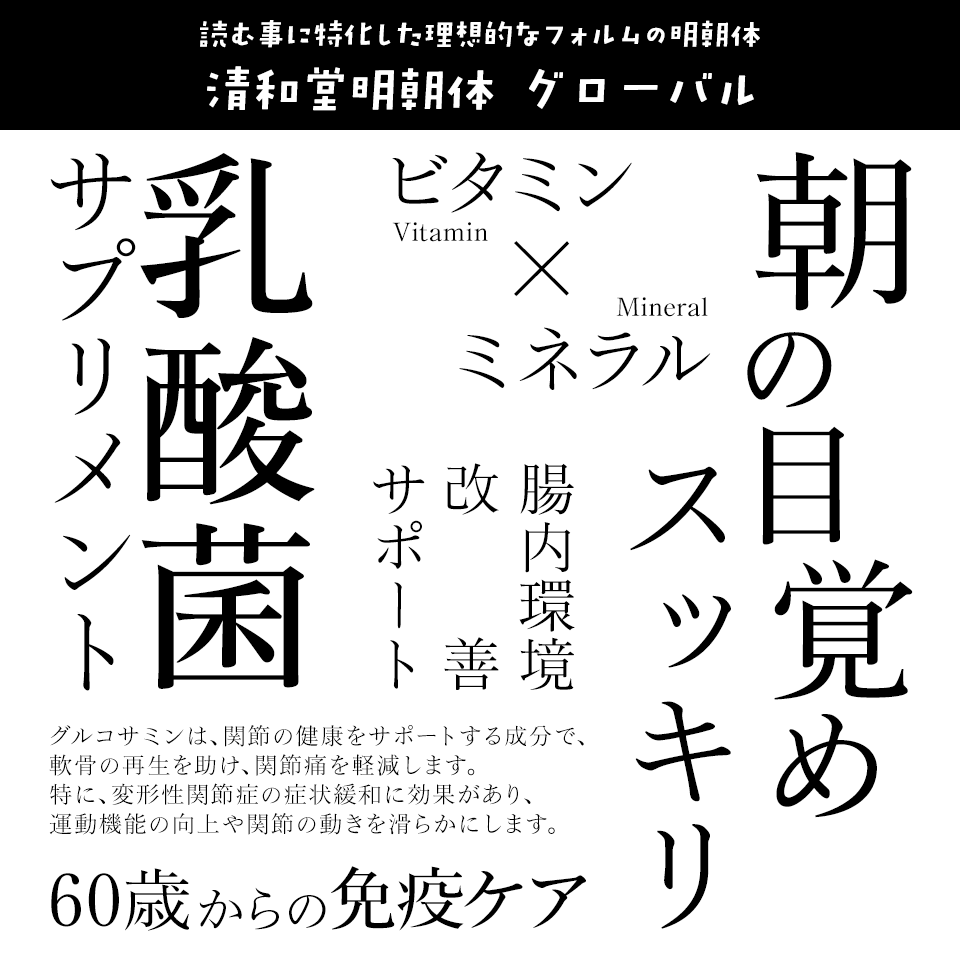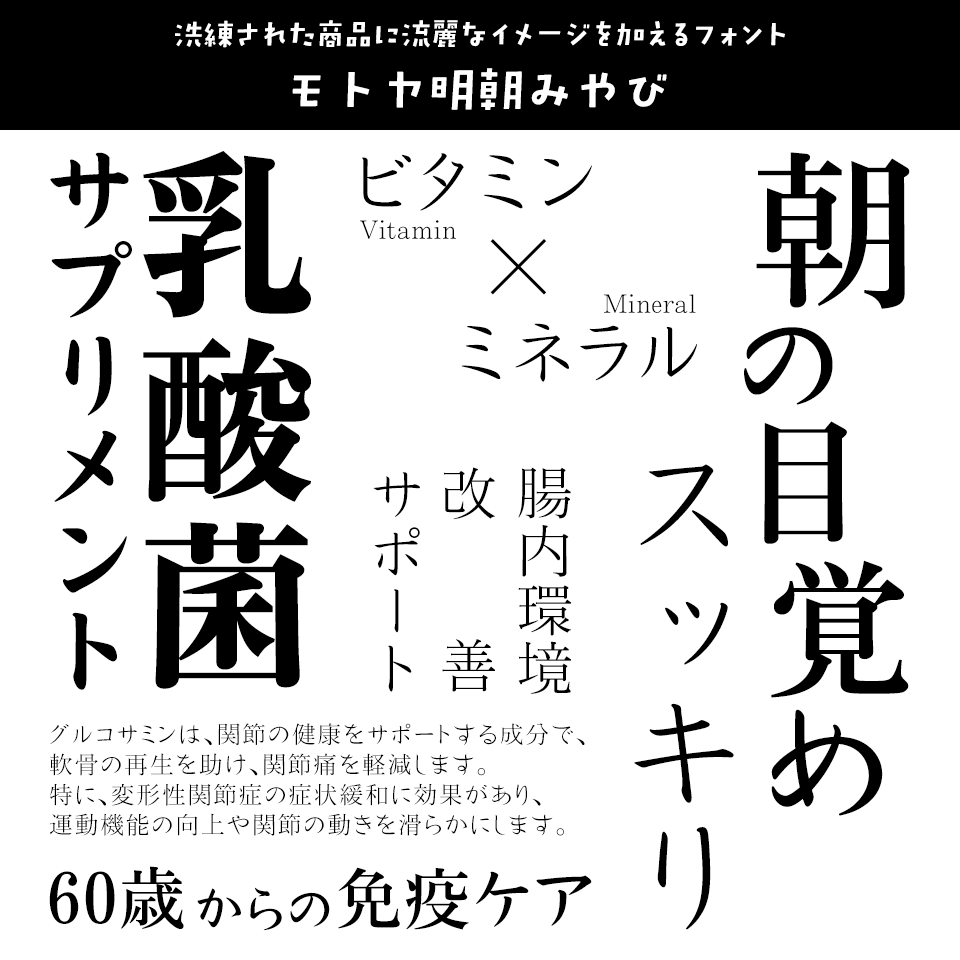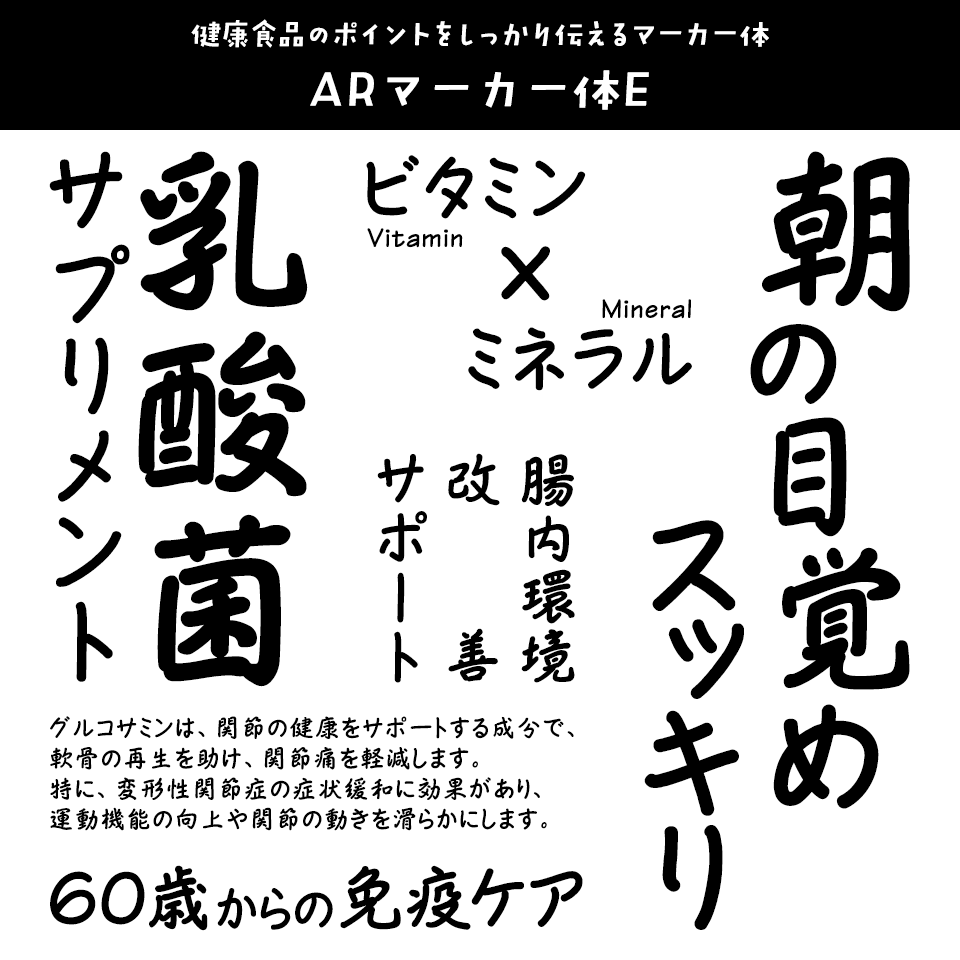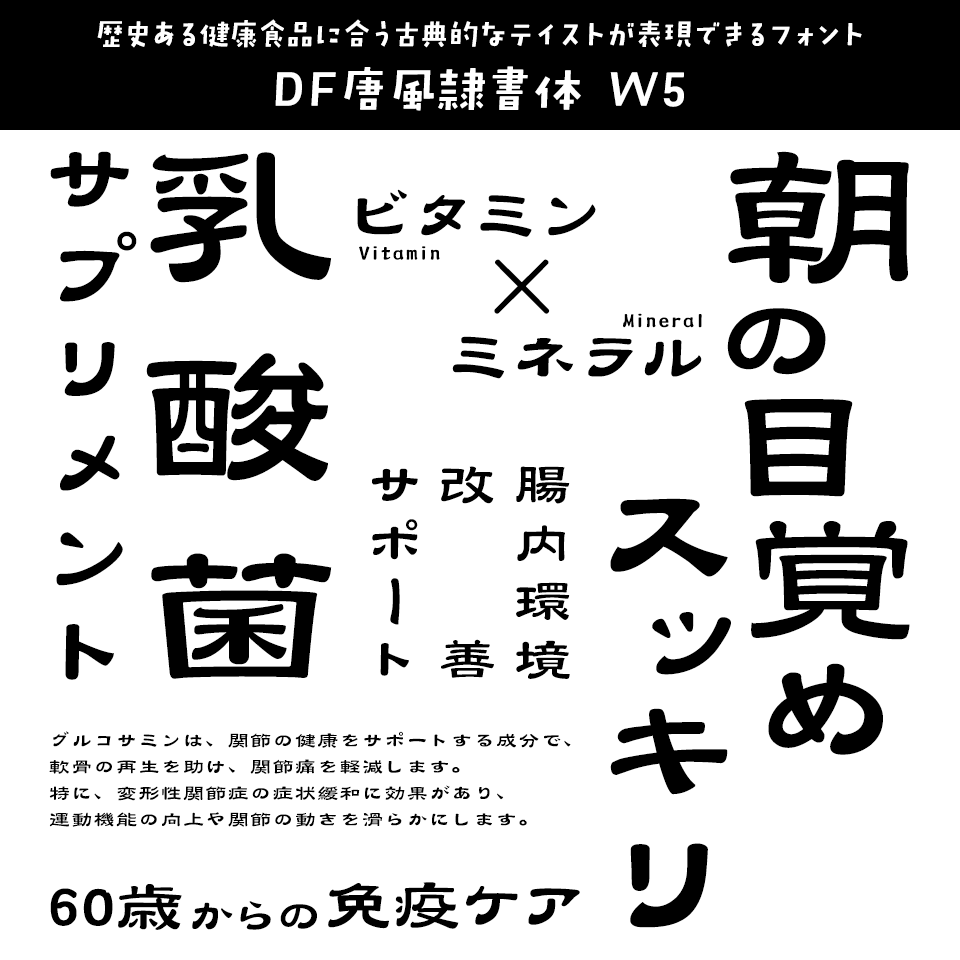
「健康食品」に合うフォント:特化型 目的別フォントガイド #143
今回は「健康食品」に合うフォント。日々フォントのことばかり考えている当店スタッフが直感的に選んだフォントをご紹介します。
「健康食品」に合うフォントをスタッフが選びました
「健康食品」に合うフォント DFひびゴシック
お悩みの訴求に使えるひびの入ったフォント
DFひびゴシック【ダイナフォント】
「健康食品」に合うフォント DFひびゴシック
健康食品の説明に不可欠なビフォーアフター。ビフォーの表現に使える不穏なひびの入ったデザインフォントです。
「健康食品」に合うフォント 清和堂明朝体 グローバル
読む事に特化した理想的なフォルムの明朝体
清和堂明朝体 グローバル【清和堂】
「健康食品」に合うフォント 清和堂明朝体 グローバル
清和堂明朝体フラッグシップ書体として、それぞれの文字固有の形を大事にしながら、標準性・汎用性、無駄がない鍛えあげたボディ、Bauhausによる「形体は機能に従う」という基本思想を追いかけ続け、読む事に特化した理想的なフォルムを追求しました。
「健康食品」に合うフォント DF娥眉明朝体
清潔感や高級感ある商品の演出におすすめ
DF娥眉明朝体【ダイナフォント】
「健康食品」に合うフォント DF娥眉明朝体
細長く弧を描いた眉の形をイメージしたストロークから洗練された女性の柔らかさや優しさを表現した明朝体の書体。清潔感や高級感ある商品の演出などに優れています。
「健康食品」に合うフォント KOはなぶさ蛍雪M
高級感のある健康食品に合う伝統に基づいたフォント
KOはなぶさ蛍雪M【欣喜堂】
「健康食品」に合うフォント KOはなぶさ蛍雪M
蛍雪『欽定全唐文』(董詰編、1814年、揚州詩局)より再生した清朝官刻体「蛍雪」、K.E.Taurus『ミラノ君主ヴィスコンティ家列伝』(1549年)より再生したオールド・ローマン体に、『少年工芸文庫第八編』(石井研堂著、1902年、博文館)より再生した和字書体「はなぶさ」を組み合わせた伝統に基づいた新たな活字書体です。
「健康食品」に合うフォント ヒラギノ明朝
チラシやLPのタイトルから本文までこなす定番の明朝体
ヒラギノ明朝【ヒラギノフォント】
「健康食品」に合うフォント ヒラギノ明朝
時代に左右されない普遍的な美しさを持ち、1993年の発売以来様々なシーンで使われ続けているスタンダードな明朝体です。 なめらかで切れ味のあるフォルムと、画線同士の空間が一定になるような細かな調整により、広告、ポスター、パンフレット、雑誌など、現代のあらゆるグラフィックデザインに調和します。
「健康食品」に合うフォント モトヤ明朝みやび
洗練された商品に流麗なイメージを加えるフォント
モトヤ明朝みやび【モトヤ】
「健康食品」に合うフォント モトヤ明朝みやび
みやびシリーズは流麗な仮名デザインで、文章に柔らかい表情を加えることができます。健康食品のパッケージや紹介文に使用すると、印象が向上すると思います!
「健康食品」に合うフォント 東亜重工 GRUNGE
グランジ加工で悩む心境を表現
東亜重工 GRUNGE【イワタ書体ライブラリー】
「健康食品」に合うフォント 東亜重工 GRUNGE
「東亜重工GRUNGE」は、東亜重工製フォント『東亜重工』にグランジ(汚れ)加工を施したフォントです。デザインソフトなしでもステッカーなどの印刷物や画像にアクセントをつけることが可能です。
「健康食品」に合うフォント イワタミンゴ
スッキリと読みやすい洗練されたモダンな書体
イワタミンゴ【イワタ書体ライブラリー】
「健康食品」に合うフォント イワタミンゴ
明朝体のシャープさ・可読性の良さと、ゴシック体の強さ・整斉さを兼ね備えた、スッキリと読みやすいデザインの格調ある書体です。
「健康食品」に合うフォント DSサラ
健康食品にぴったりのナチュラルな書体
DSサラ【七種泰史/デザインシグナル】
「健康食品」に合うフォント DSサラ
さらりサラサラ。すっきり、あっさり味の書体。健康食品のイメージに合う細めでナチュラルな印象のデザインが特徴です。
「健康食品」に合うフォント DF平成ゴシック体R W7
説得力なら太めのゴシック体
DF平成ゴシック体R W7【ダイナフォント】
「健康食品」に合うフォント DF平成ゴシック体R W7
健康食品の効能に説得力を持たせるのにぴったりな太めのゴシック体です。
「健康食品」に合うフォント ARマーカー体E
健康食品のポイントをしっかり伝えるマーカー体
ARマーカー体E【アーフィック】
「健康食品」に合うフォント ARマーカー体E
見出しやタイトル、吹き出しのコメントなど、健康食品のチラシやLPの様々な場所で使いやすいフェルトペンで書いたタッチの手書き風書体です。
「健康食品」に合うフォント TA 石ちゃん
ガラガラと崩れる健康状態に
TA 石ちゃん【FONT1000】
「健康食品」に合うフォント TA 石ちゃん
大きな石を削って文字を作ったイメージです。荒々しいフォルムですので、フォント名は逆に馴染み易くしました。崩れる生活習慣のに、粗削りな輪郭のフォントを。
「健康食品」に合うフォント DF唐風隷書体 W5
歴史ある健康食品に合う古典的なテイストが表現できるフォント
DF唐風隷書体 W5【ダイナフォント】
「健康食品」に合うフォント DF唐風隷書体 W5
横長で太く扁平な字形がどっしりと落ち着きを感じさせる「隷書体」です。中華風を表現したい場面や古典的なテイストの表現したい場面などに適しています。
「健康食品」に合うフォント イワタ福まるごカタル
柔らかいフォルムが「体に優しい」健康食品に合う丸ゴシック
イワタ福まるごカタル【イワタ書体ライブラリー】
「健康食品」に合うフォント イワタ福まるごカタル
映画字幕などで使われていた特徴的な文字をモチーフにした書体です。線画が長く高低差の少ない骨格と、線端の抑揚が手書きのイメージを伝えます。レトロな映写機で映し出された名作が優しくゆっくりと語りかけるかのようです。
「健康食品」に合うフォント パンダベーカリー
子供用健康補助食品のLPにぴったりかわいいデザインフォント
パンダベーカリー【鈴木メモ】
「健康食品」に合うフォント パンダベーカリー
2018年秋の発売以来、SNSでも話題の大人気のフォントです。手描きのリズムを活かした、カジュアルで太めの日本語フォントです。
「健康食品」に合うフォント 花とちょうちょ
パッケージデザインにも使ってほしい手書きフォント
花とちょうちょ【鈴木メモ】
「健康食品」に合うフォント 花とちょうちょ
SNSで話題沸騰中の大注目のフォントです。ペンで右上がりに書いた手書き文字から作った、ちょうちょのように軽やかな日本語フォントです。写真やイラストに書き込みをしたように傾けたレイアウトで使用するのもおすすめです。美容系食品のパッケージにも